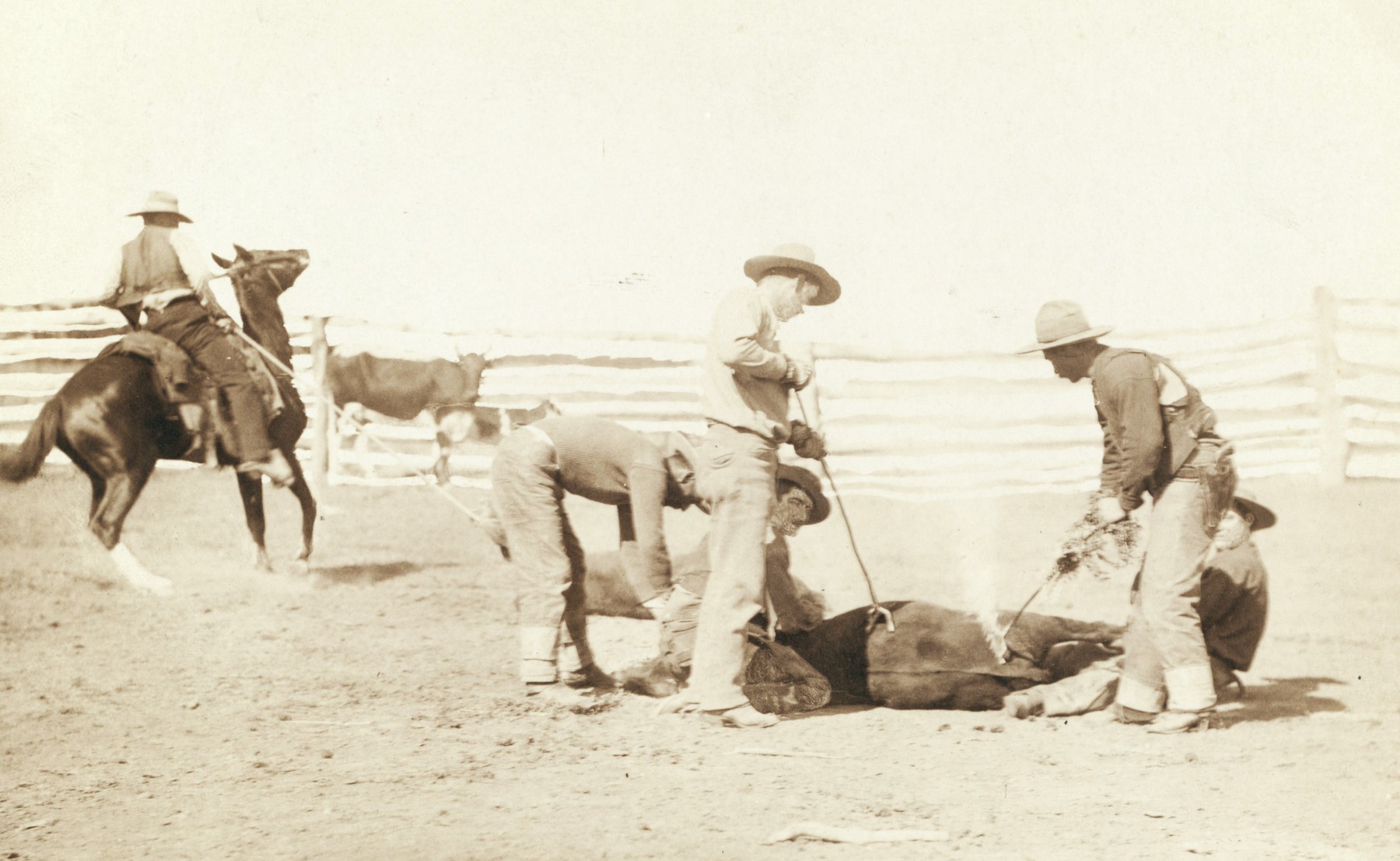
Abécédaire d’icônes
Abécédaire typographique avec des icônes d'Ipad
Nous vous parlions de la tendance actuelle du design à simplifier les symboles des marques. Les logotypes deviennent des icônes et s’adaptent à l’affichage des interfaces tactiles de nos tablettes et smartphones pour devenir des « apps » : formes épurées et contraste chromatique accentué assurent leur lisibilité en petites tailles… quitte à ressembler à des touches de clavier ? En tous cas idéal pour être pressé sous nos gros doigts !
Dans la continuité de cette logique là, Joe Kissel, un chroniqueur de « nouvelles technologies » s’est bien amusé, il a compilé différentes applications, dont les icônes sont composées d’une lettre pour créer un alphabet complet. On obtient une sorte de machine à écrire sponsorisée. Fallait y penser !
On peut noter que la France est représentée à la lettre « v », par l’application de « Voyages SNCF » !
L’histoire ne raconte pas combien lui a coûté cette idée en applications !
Blague de graphiste
Attention blague de graphiste en vue ! Effectivement il sera impossible au quidam de comprendre se qui se cache derrière ces successions de lettres « ups », « Ai » et « eps ». Preuve en est que des effets « web 2.0″ sur un joli blason ajoutés à un code couleur, soi-disant pérenne, ne remplace pas le célèbre ruban cadeau que Paul Rand a dessiné en 1961.
Eps pour Encapsulated PostScript, est un format créé par Adobe Systems qui permet de décrire des images qui peuvent être constituées d’objets vectoriels et/ou bitmap. Ce format est principalement utilisé par Adobe Illustrator (Ai).
Ajourd’hui, il existe tellement de similitudes (et si peu de distinctions !) entre l’identité visuelle de l’entreprise postale américaine UPS et l’icône du logiciel de dessin vectoriel de la creative suite d’Adobe, qu’il serait bien difficile de deviner le service que ces deux entités sont censées rendre !
Voici quelques étapes importantes dans l’évolution du logo UPS et celui d’Adobe Illustrator :
En mettant de côté les effets de reliefs que facilite l’affichage à l’écran, ce rapprochement illustre une tendance forte du graphisme actuel :
La simplification des symboles des marques qui va de pair avec une importance croissante du dessin des caractères. Les logotypes deviennent alors des icônes et s’adaptent à l’affichage des interfaces tactiles de nos tablettes et smartphones pour devenir des « apps » : formes épurées et un contraste chromatique accentué assure leur lisibilité en petites tailles… quitte à ressembler à des touches de clavier ? En tous cas idéal pour être pressé sous nos gros doigts !
Paul Rand parlait ainsi de son travail :
« Je n’utilise pas l’humour consciemment, c’est quelque chose de naturel. Le meilleur exemple est mon logo pour United Parcels Service: prendre un écusson – un symbole médiéval qui semble inévitablement pompeux aujourd’hui – et puis coller un paquet au-dessus, c’est drôle »…
C’est probablement dans cette simplicité et cet humour que résidait toute l’intelligence du travail de Paul Rand.
Pour savoir quelles raisons ont poussé UPS à changer de logo en 2003, on peut retrouver sur le site Underconsideration.com le kit de presse annonçant le changement de logo ( ici ). L’argument qu’ils avancent à l’époque était « Pour un impact visuel encore plus grand, le bouclier est devenu trois dimensions« , ce qui peut se traduire par « Le logo de Paul Rand était faible, mais en passant en 3D le nouveau logo devient fort ! ».
Ça se saurait depuis longtemps si passer en 3D un logo lui donnait plus d’impact !
La principale conséquence, c’est d’augmenter les coûts de reproduction !
Les logos de Paul Rand : http://www.paul-rand.com/foundation/identity/
Mise à jour du 26/02/2013
Le site d’actualité en identités visuelles BRAND NEW vient de publier un article intitulé « Des logos réduits pour l’utilisation sur écran » (Logo Reductions for Screen en VO). Ils présentent le résultat d’un sujet qui a été donné aux élèves de l’institut de technologie de Holon lors d’un cours de design interactif. L’objectif était d’adapter la version « print » d’un célèbre logotype pour en faire une utilisation à l’écran : icône de lancement d’application, favicon, visuel pour écran d’ouverture, etc… Voici le résultat de ces étudiants qui ce sont attaqués aux célèbres logos de Quaker, Unilever, Energizer et Ikea :
reduction_logo_for_screen
Une préoccupation très actuelle !
Petite histoire du mot Branding !
étude du sens du mot branding en rapport avec son histoire
Qu’est-ce qu’une marque ?
Les Anglo-saxons la nomment « brand », Branding étant l’activité consistant à concevoir des « marques ».
Ce terme s’est massivement imposé dans le jargon professionnel, au point de ne m’être jamais questionné sur le sens profond de ce mot. Pourquoi la traduction du mot français « marque » n’est-elle pas « mark » ?